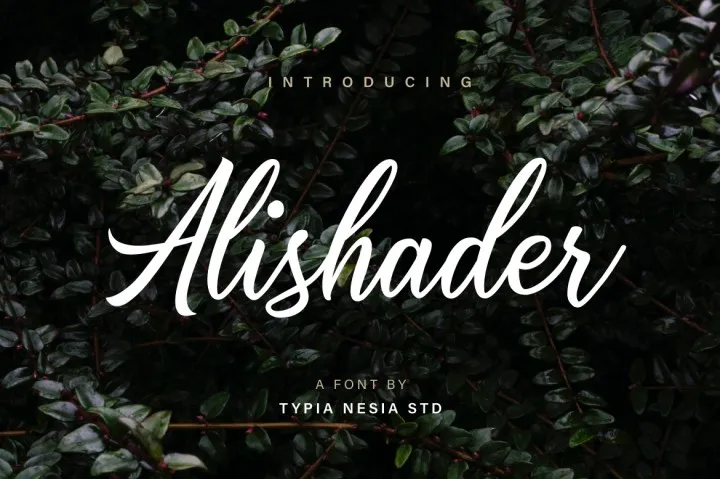
Alishader Script Font – Download Grátis
Alishader é uma fonte script elegante e moderna, criada pela Designer Hamilton. Suas linhas fluidas remetem a velhos cadernos de arte, combinando os elementos do chamado e da escrita cursiva. Essa fonte foi projetada para atender um amplo espectro de projetos, incluindo cartões de convite modernos, marcas de marca, estaçãoaria, blogs, design publicitário moderno, cartas de convite, lemas artísticos, decoração em casa e até mesmo o título dos livros ou capas. Suas linhas delicadas e fluidas são perfeitas para qualquer requinte da escrita chamada que você possa precisar. Não importa se é um convite de casamento especial, uma festa de aniversário ou qualquer outro evento a ser celebrado com elegância e estilo moderno. Alishader está aqui para ajudar em todos esses projetos.